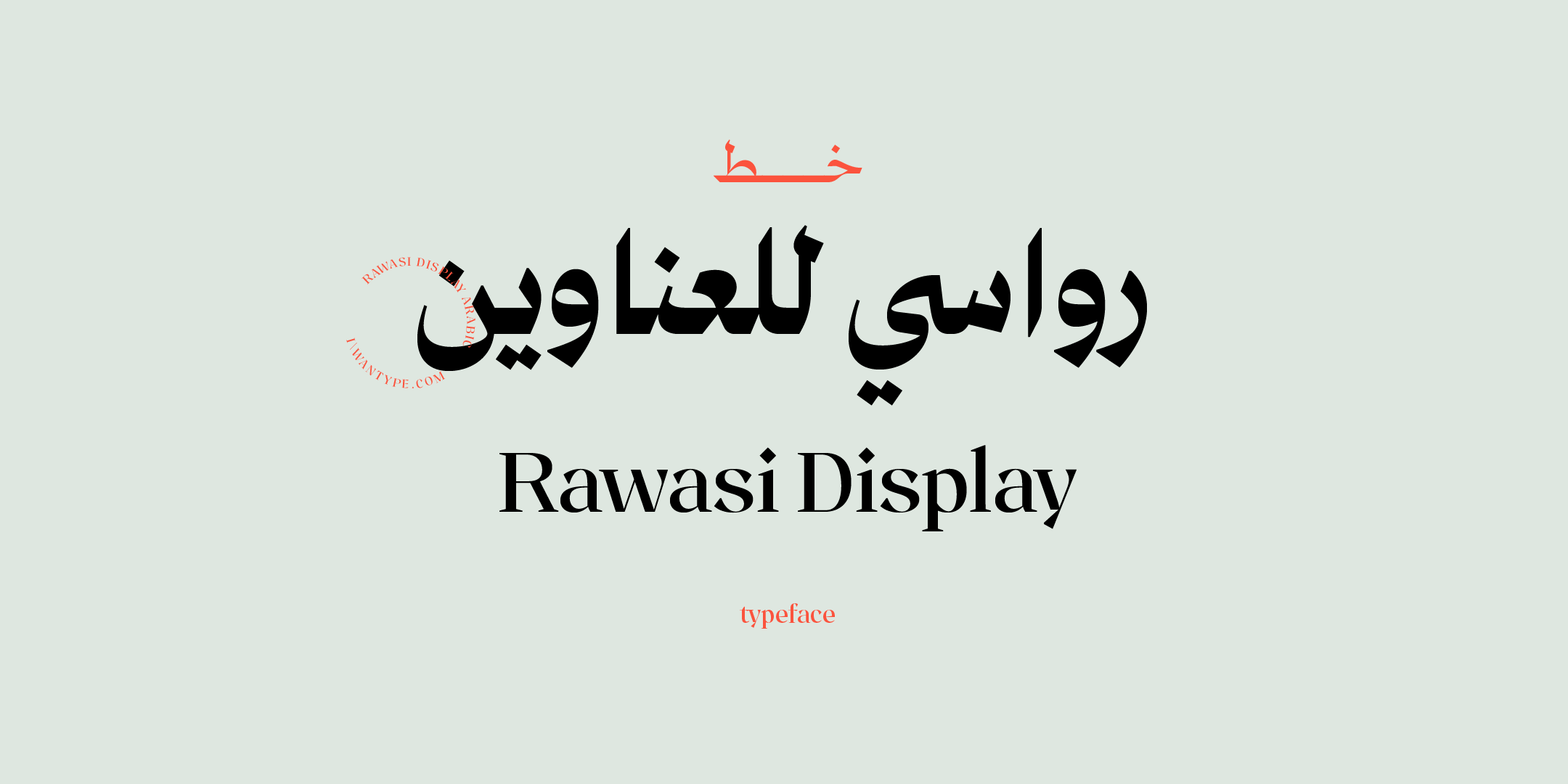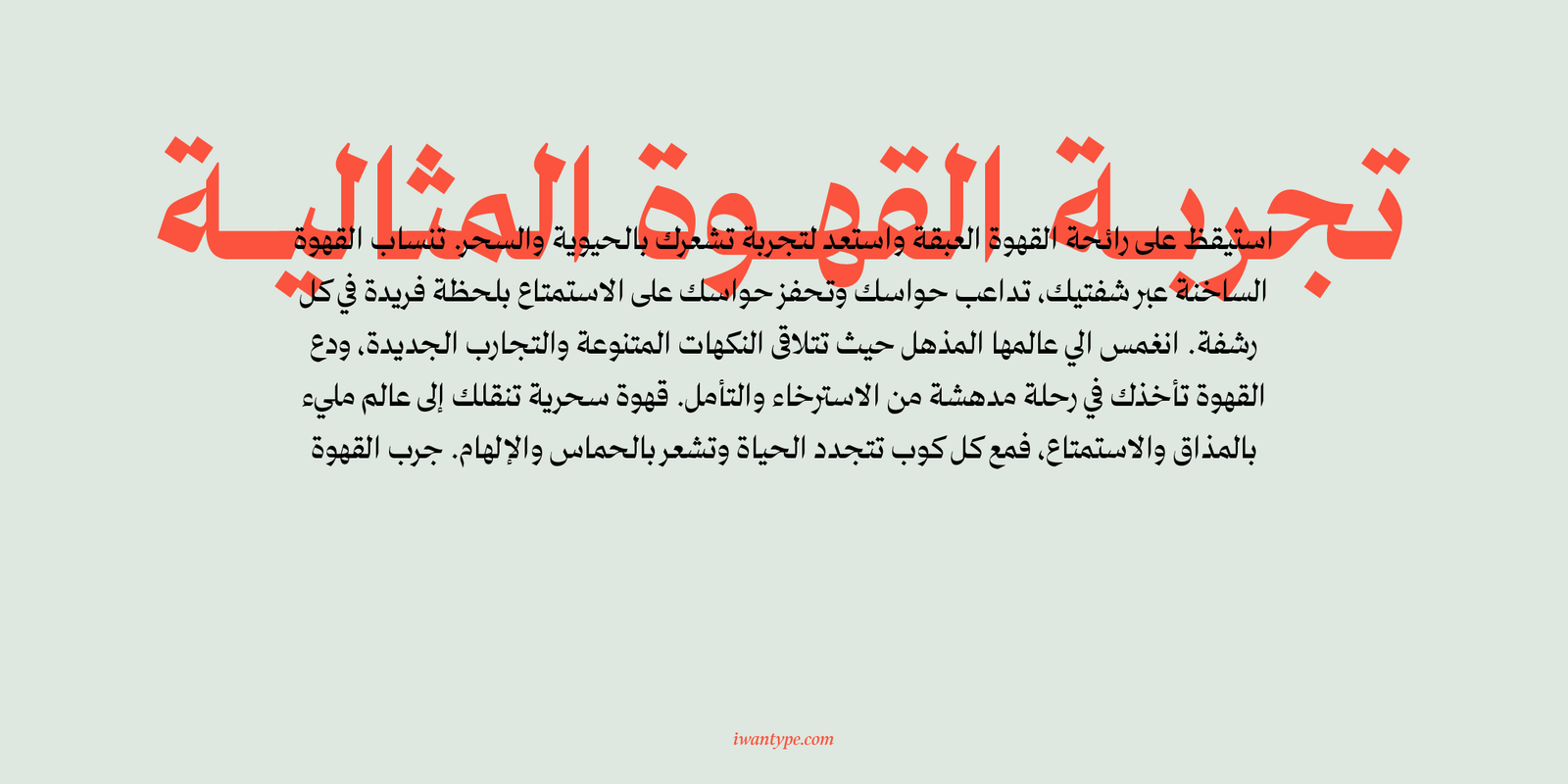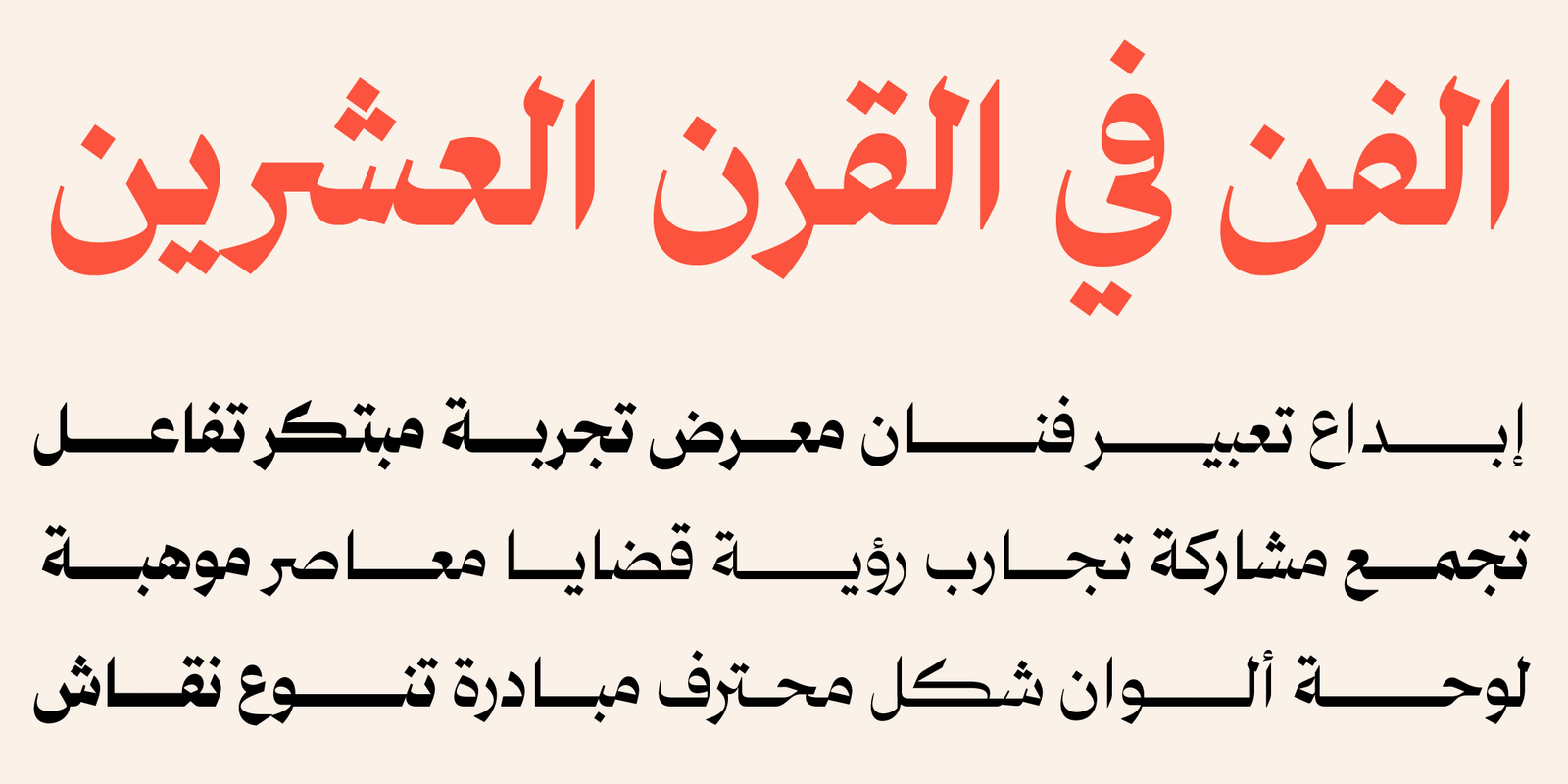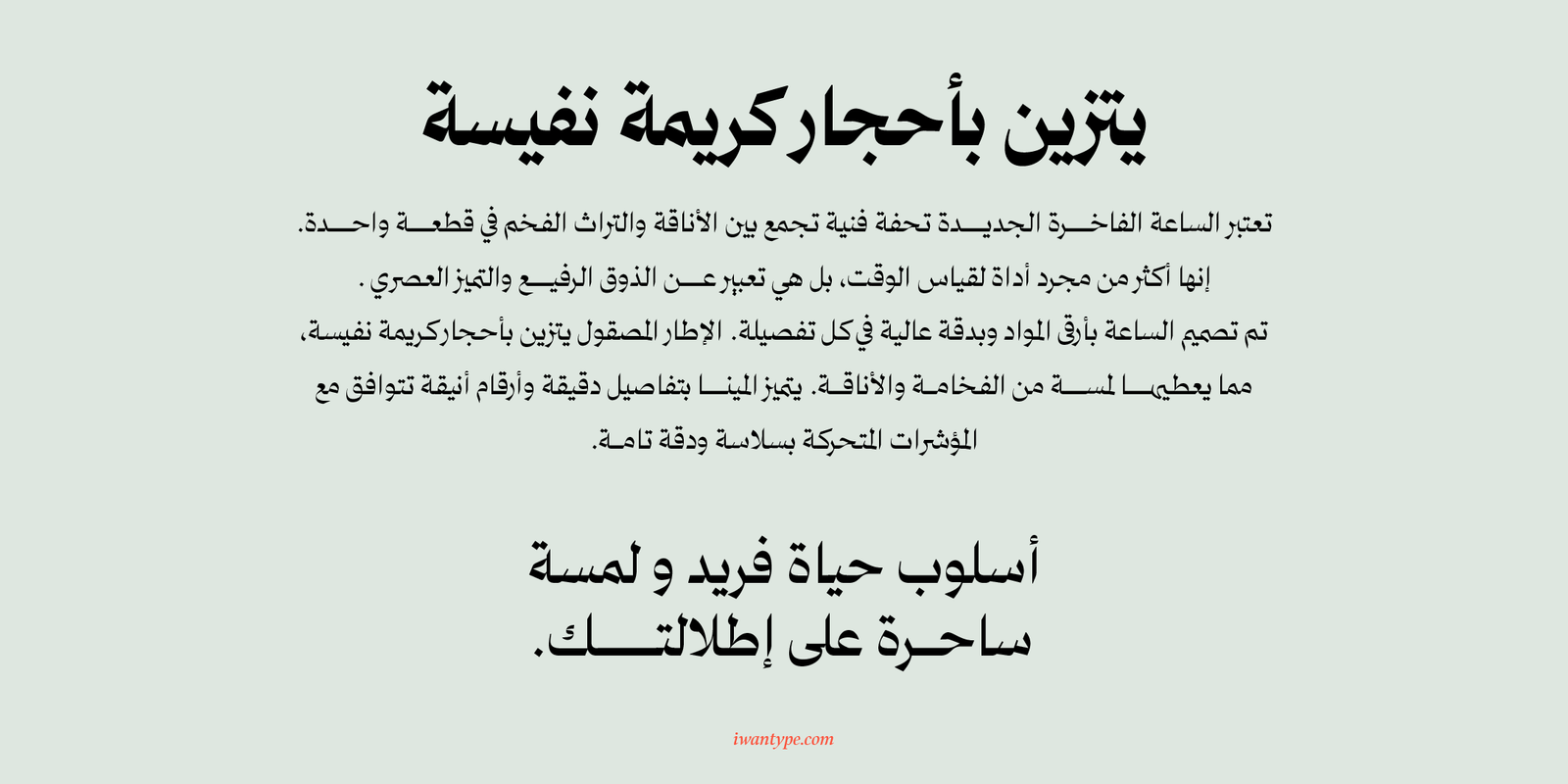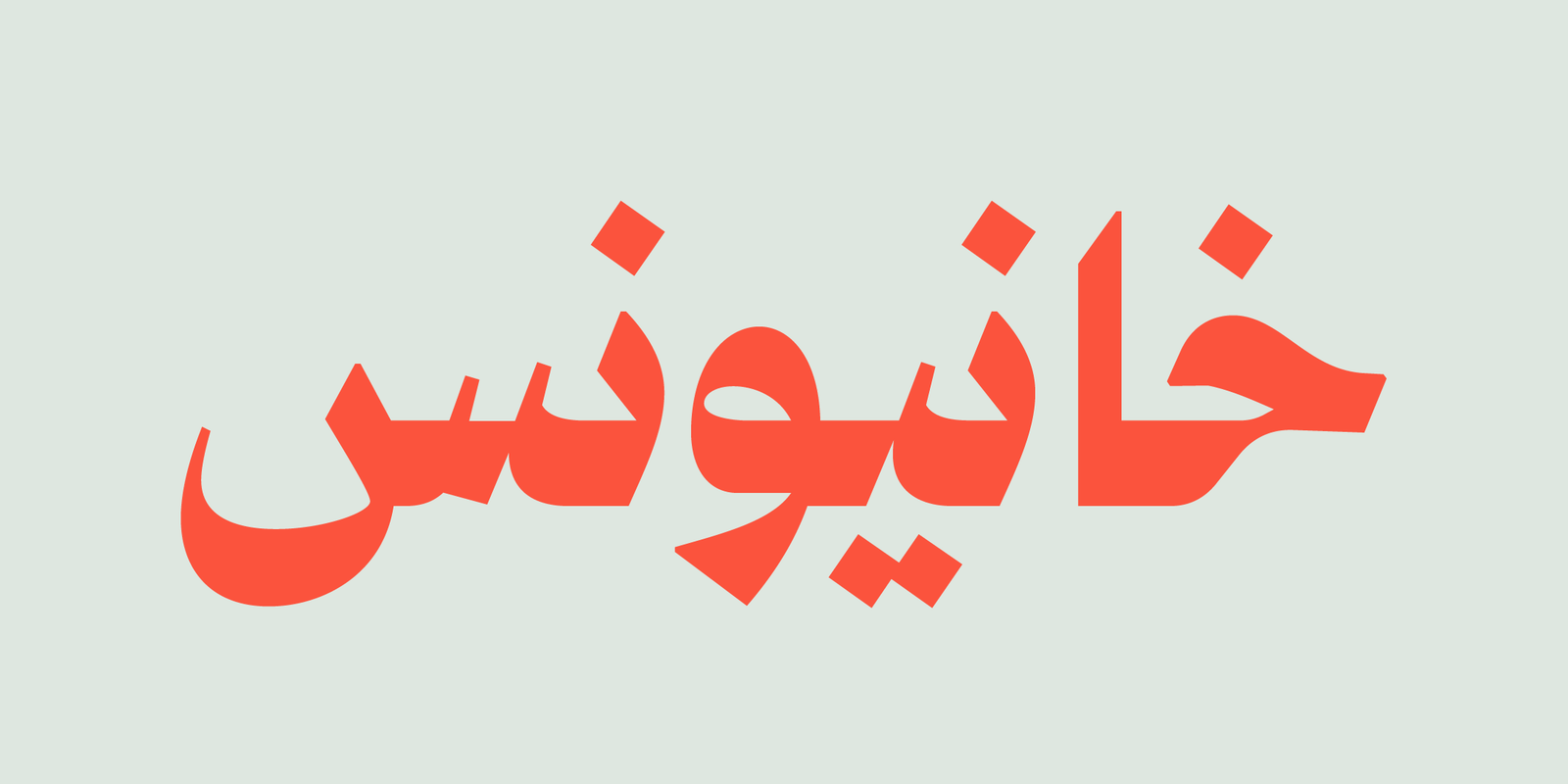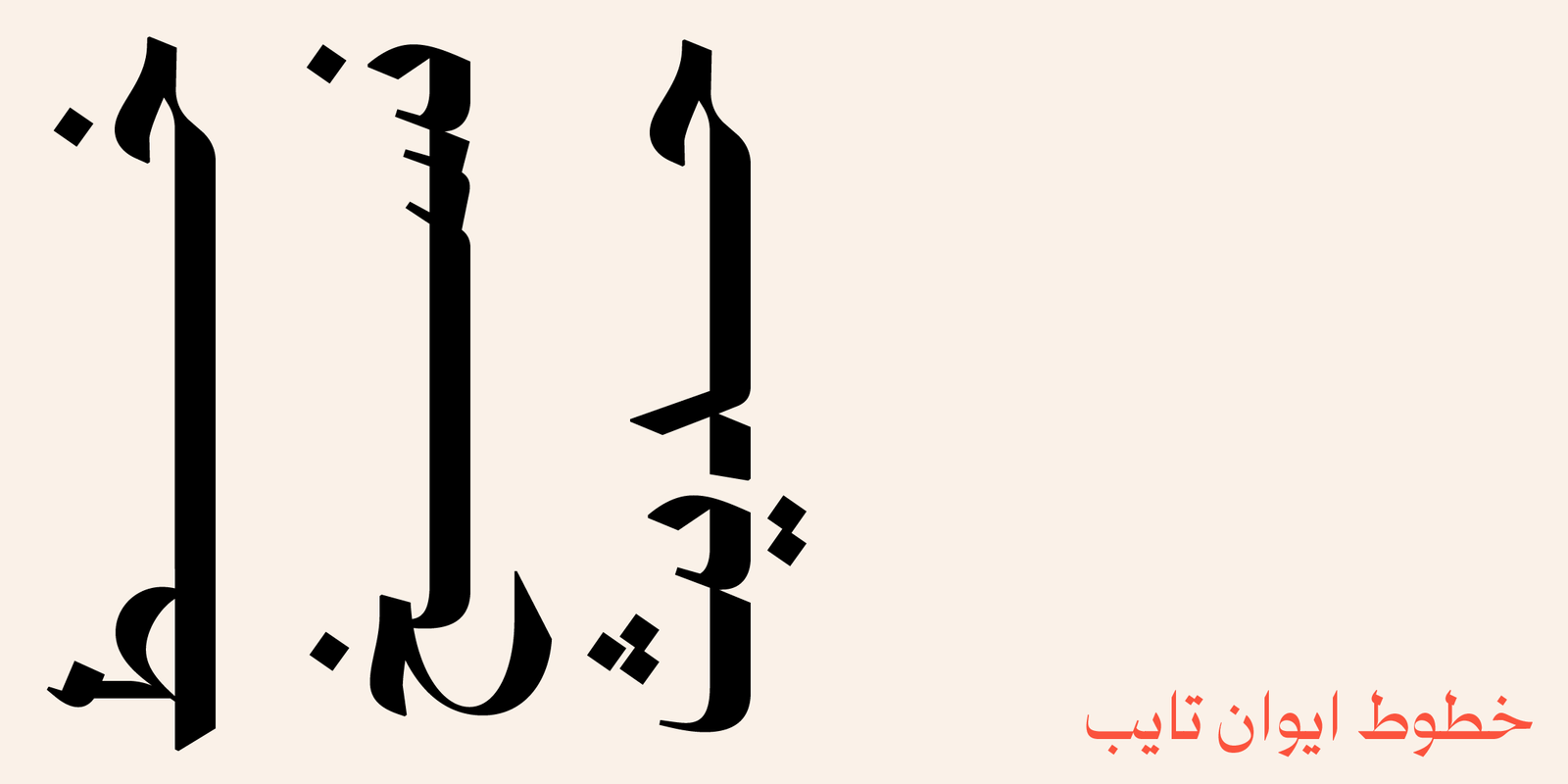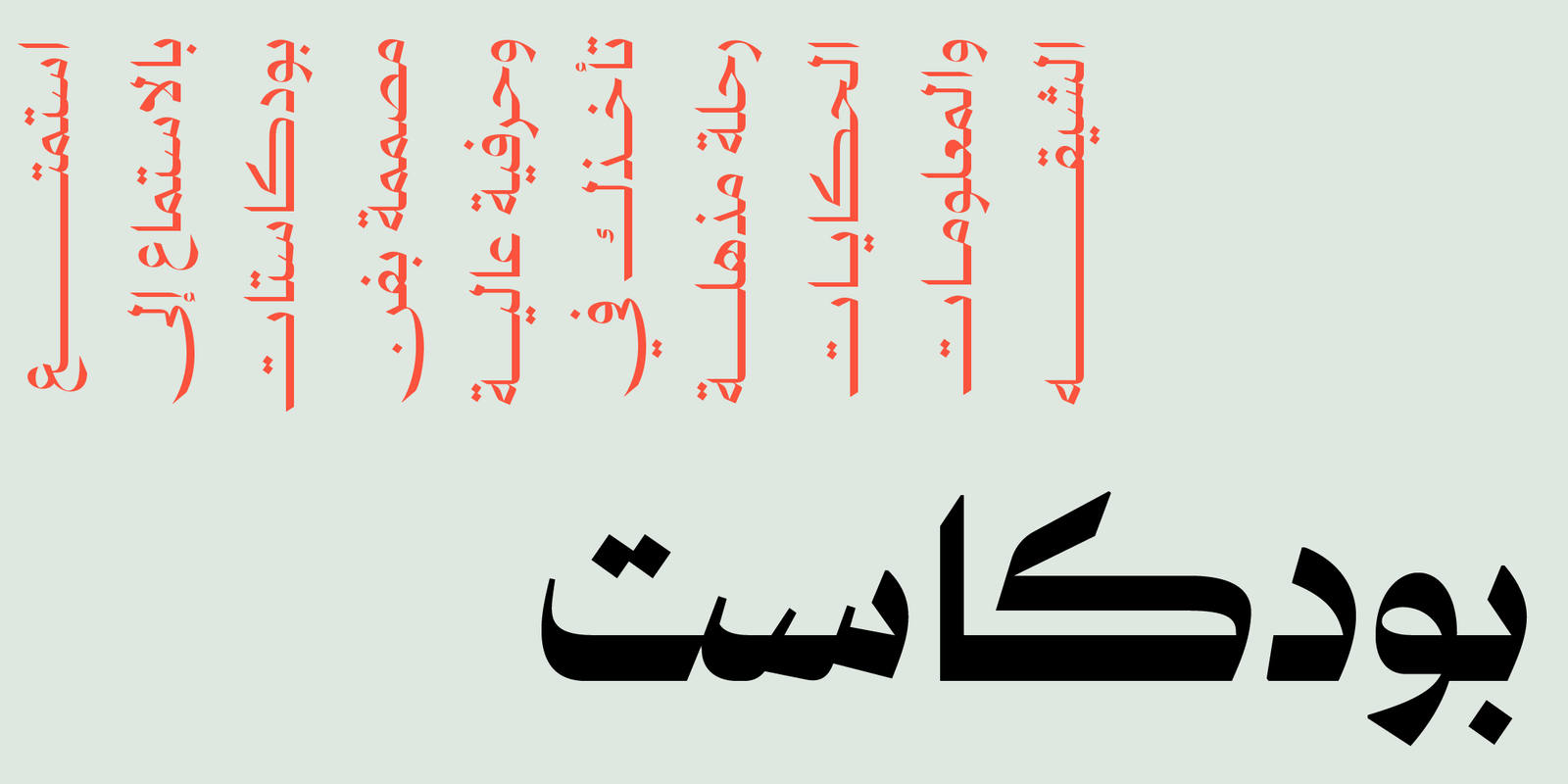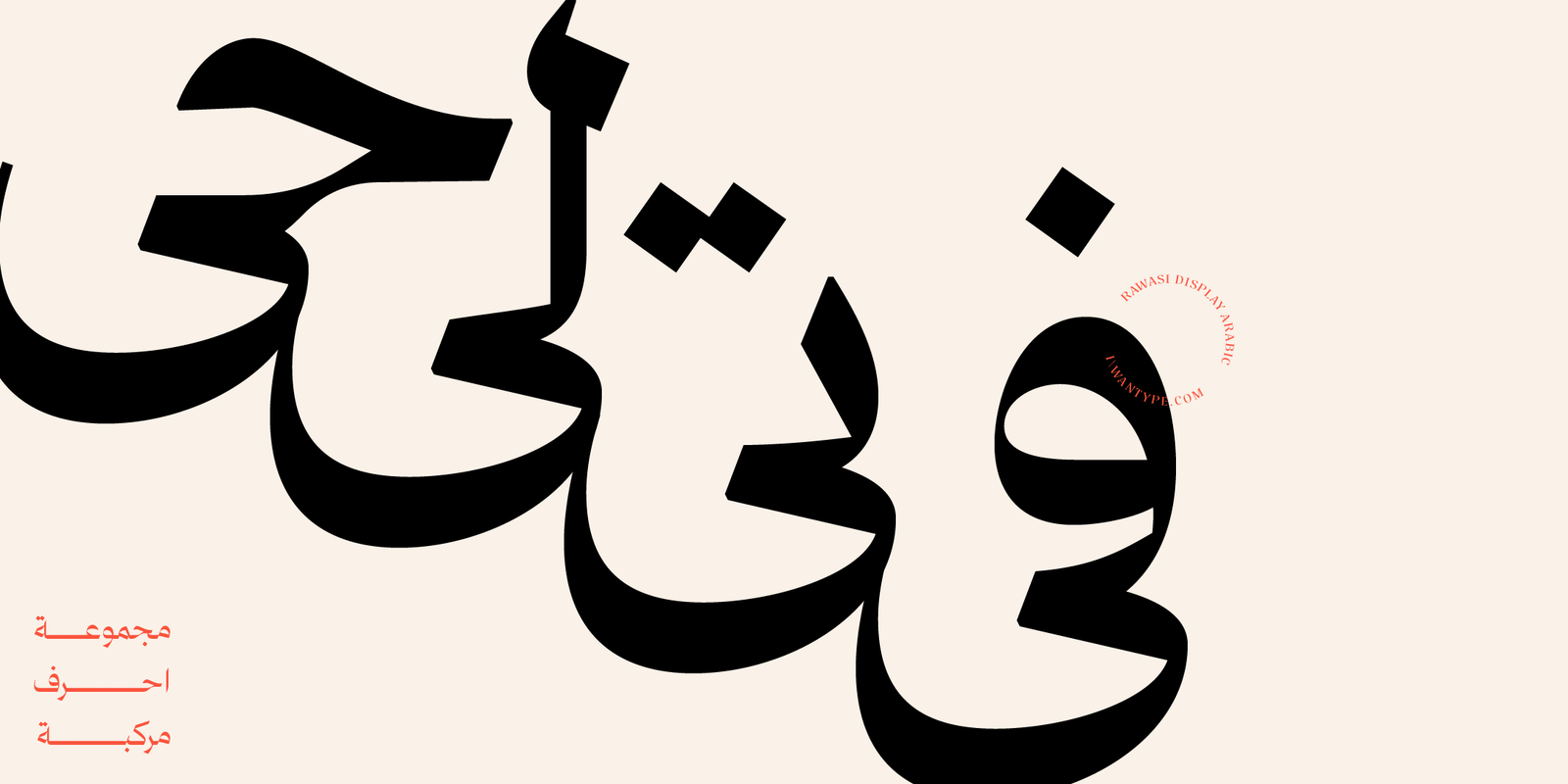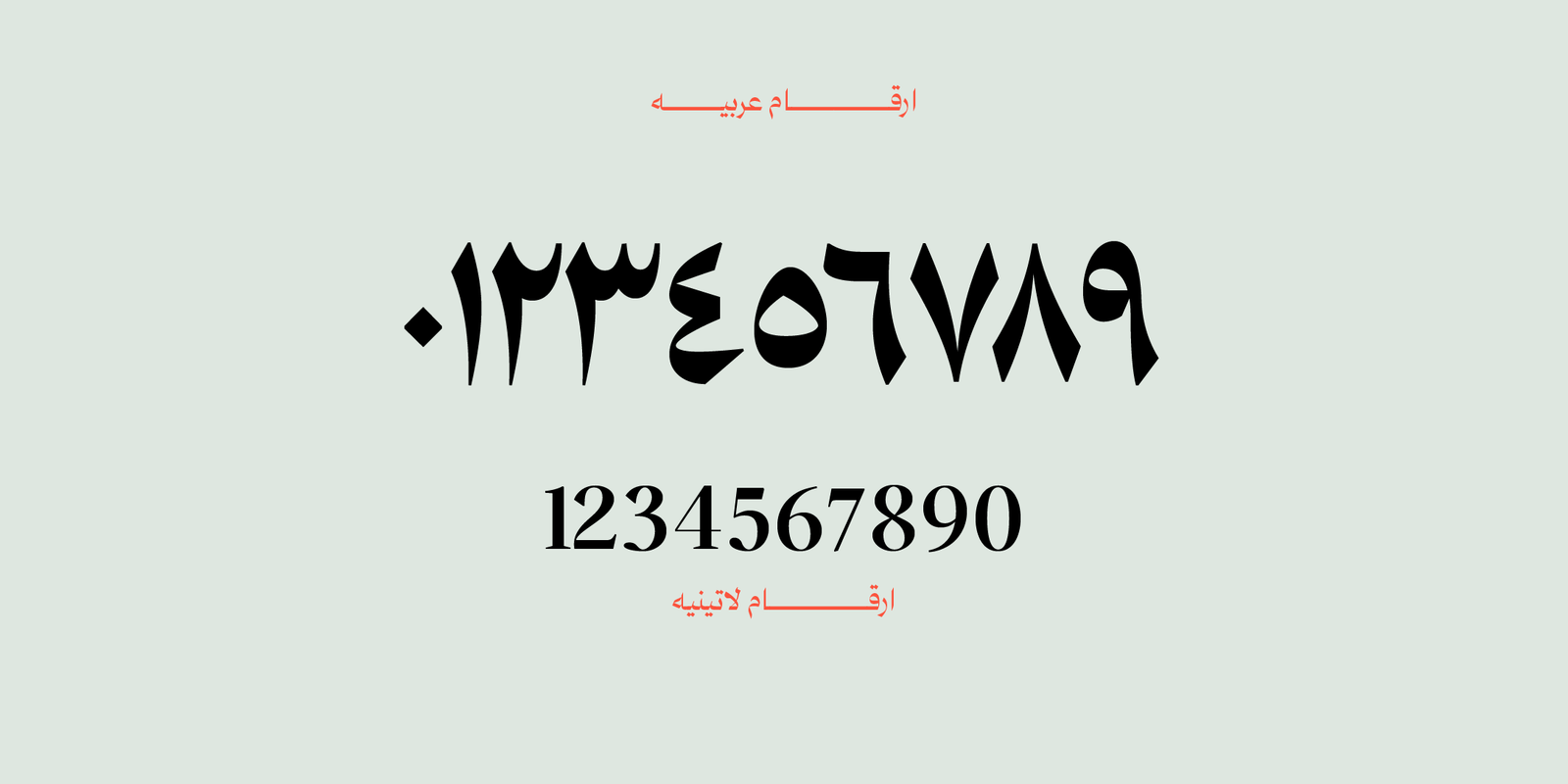
Rawasi Display Typeface – خط رواسي للعناوين
Rawasi Display Typeface – خط رواسي للعناوين : خط عربي فخم وحديث
رواسي للعناوين هو خط طباعي يجمع بين التصميم التقليدي والحديث. بحواف حادة وتباين جذاب، يُضيف هذا الخط لمسة فاخرة وحديثة لأي تصميم. مع تفاصيله المميزة من مجموعة أوبن تايب، مثل الحروف المركبة، يُقدم لك تجربة طباعية فريدة. ببساطة.
مميزات خط رواسي للعناوين:
يتضمن الخط العديد من مزايا OpenType التي تضفي عليه مرونة وتنوعًا في الاستخدام، مثل:
- أحرف مرسلة (تُفعَّل بإضافة “ءء” بعد الحرف)
- أحرف مركّبة تُحسّن سلاسة التراكيب وتناسق النص.
- يدعم رمز الريال السعودي والريال العُماني ،ويتم تفعيلهما تلقائيًا عند كتابة الاختصارات: ر.س للريال السعودي ر.ع للريال العُماني
اللغات: العربية والانجليزية
الاوزان : ٦ أوزان